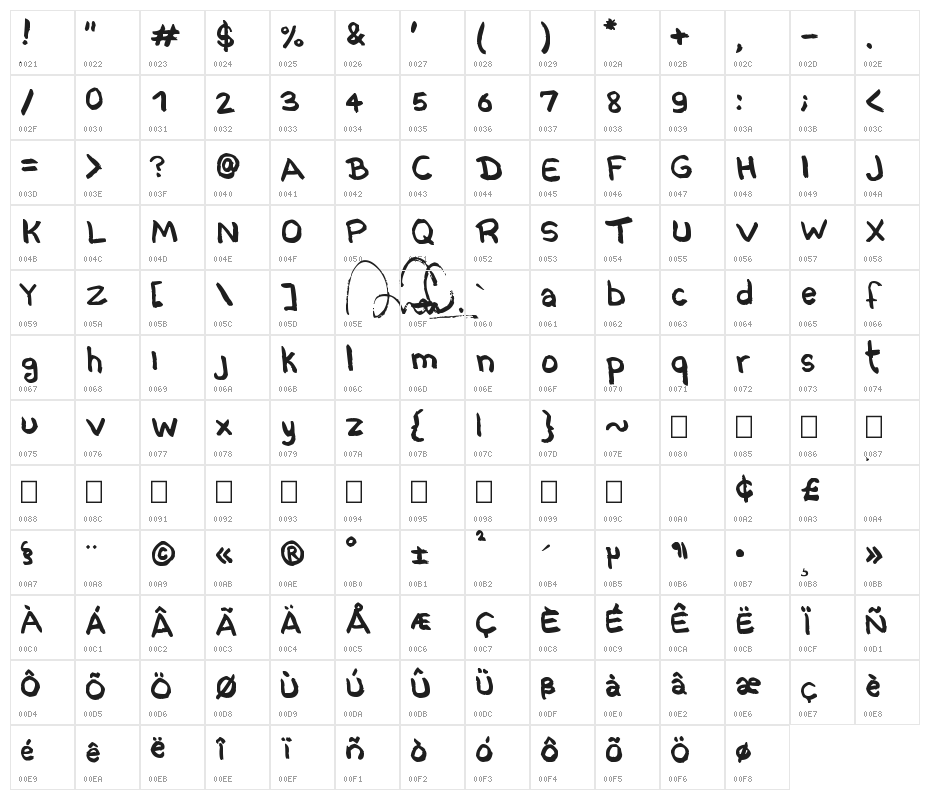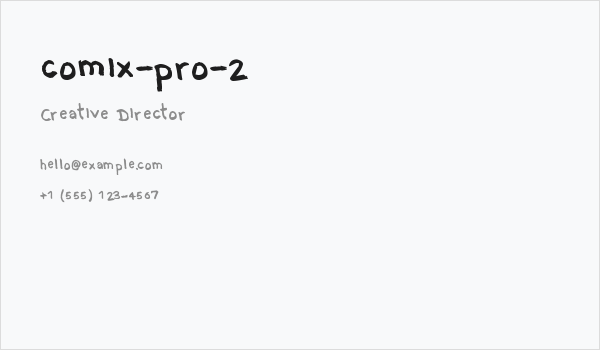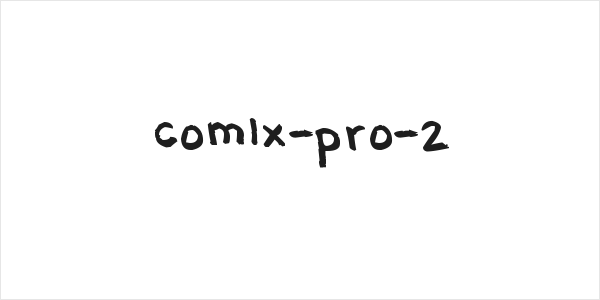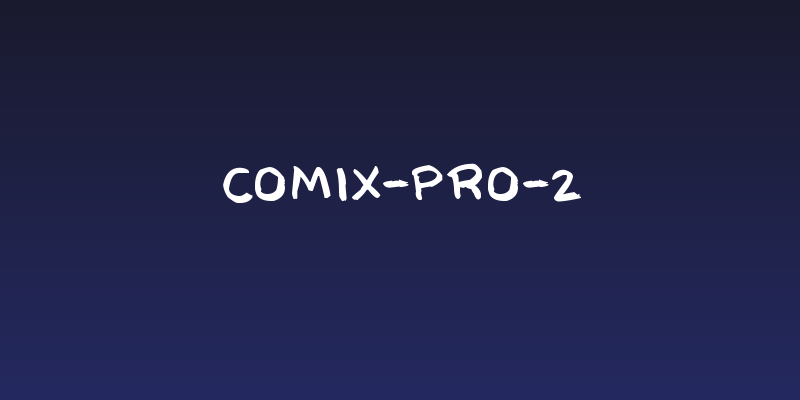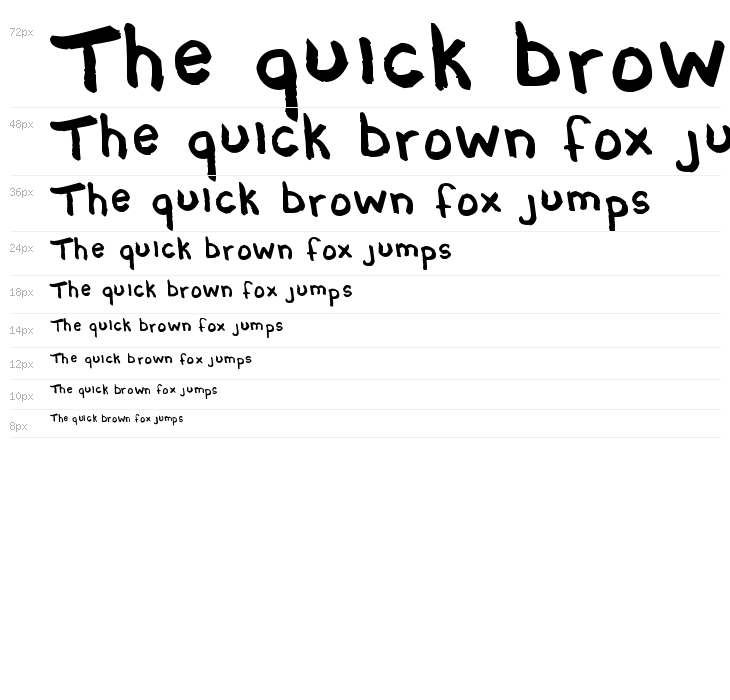
comix-pro-2 Font
| Stile generale | Playful, Informal, Comic |
| Progetti proposti | Ideal for comic books, children's books, playful branding, posters, and social media graphics. |